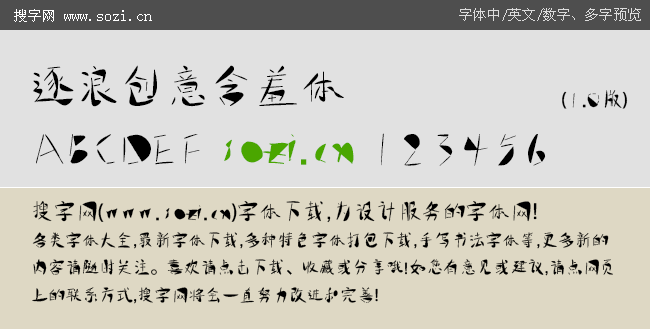
逐浪創(chuàng)意含羞體
搜字網(wǎng)提供一款逐浪創(chuàng)意含羞體中文藝術(shù)字體下載,逐浪創(chuàng)意含羞體是一款非常個性的中文創(chuàng)意字體,該字體創(chuàng)意十足、個性鮮明,整體效果十分出色。適合應(yīng)用于廣告設(shè)計、名片設(shè)計、包裝印刷、產(chǎn)品設(shè)計等應(yīng)用。本字體僅供個人學(xué)習(xí)使用,如需商用請聯(lián)系作者進(jìn)行購買(作者主頁http://www.ziti163.com/index.shtml)。